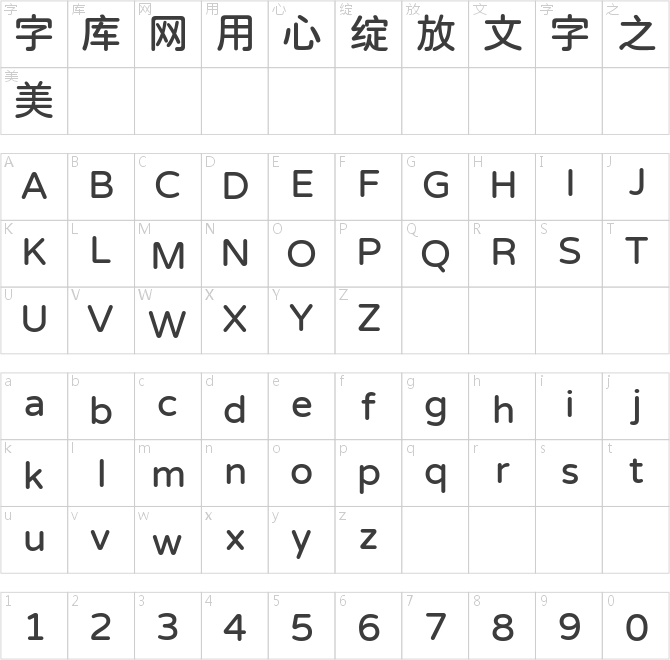
字體名稱: 極影毀片熒圓
極影毀片熒圓
極影毀片熒圓介紹
極影毀片熒圓是一款使用小杉圓體為底本,使用未來圓進行增補的自由字體。
jfopen粉圓是繁體中文基準的字體,而繁體中文的字體都存在字形標準 不一而造成的字形混亂問題。
比如草字頭、走之旁、絞絲旁、令字的寫法、羽宇的寫法、戶字的寫法等等。
甚至同一字體里面,同一偏旁字形都會存在 兩種不同的寫法。這造成了極影毀片圓后續維護的龐大壓力。
極影毀片圓采 用了鄙人手動修正字形來解決上述問題,但不可避免會使得字的重心更加混亂。
所以我產生了放棄粉圓,直接使用小杉圓體作為底本,同時直接使用簡 體中文字形的思源系圖體來增補,
以達到大幅減少后續維護目的的重制極影 毀片圓的想法。 未來熒黑是將思源黑體進行拔腳,并重新調整字的重心的字體。
由未來 熒黑修改而成的未來圓,在字形上最為接近小杉圓體本來的樣子。所以我采 用了未來圓作為增補使用的字體來源。
具體的操作如下。首先我將小杉圓體的字分為兩組,一組是GB2312已經收錄的字,另一組是其他的字。
后者直接收錄,前者手動挑選字形和規范字寫法相同或十分相近的字保留收錄,其余日本漢字字形的漢字放棄。
剩余的漢字將未來圓稍稍橫向拉伸后增補。